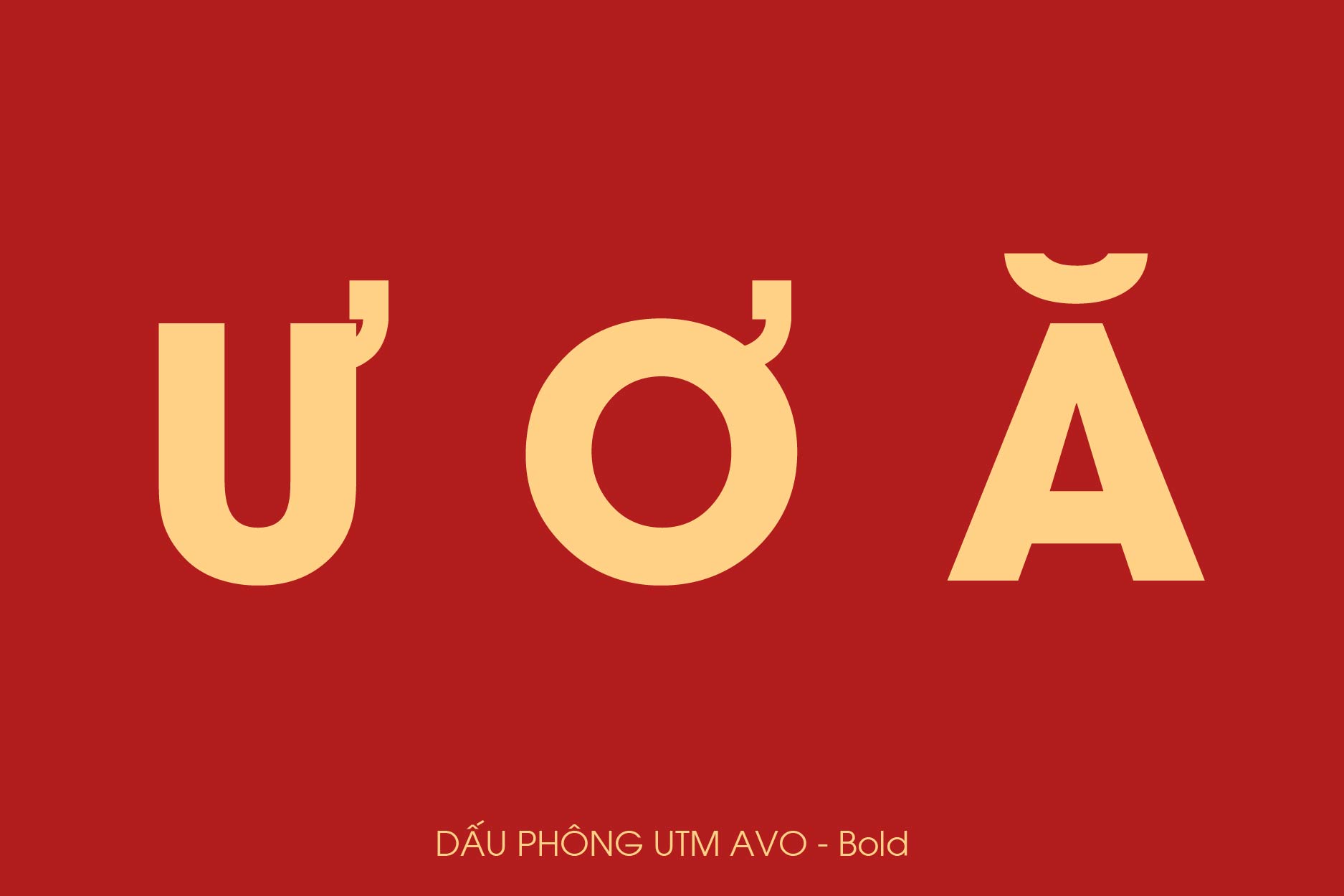
Font SVN Avo việt hóa là font chữ sans-serif hiện đại, thanh lịch thuộc bộ font SVN phổ biến trong giới designer Việt Nam. Font chữ này được sử dụng rộng rãi trong thiết kế thương hiệu, poster quảng cáo, website và tài liệu doanh nghiệp nhờ nét mảnh, chuyên nghiệp và khả năng hiển thị tốt trên mọi nền tảng.
Font SVN Avo việt hóa là gì?
Font SVN Avo thuộc bộ font SVN (SVN Fonts Việt Nam) được thiết kế với phong cách hiện đại, minimalist, mang hơi hướng của các font sans-serif geometric phương Tây. Font này đặc biệt phổ biến trong giới designer Việt Nam nhờ sự kết hợp hoàn hảo giữa tính thẩm mỹ và khả năng hiển thị tốt trên cả màn hình và in ấn.
SVN Avo có nét mảnh, thanh lịch với các đường nét cân đối, tạo cảm giác nhẹ nhàng nhưng vẫn đủ mạnh mẽ để làm nổi bật thương hiệu. Font này tương thích đầy đủ với tiếng Việt, hỗ trợ tất cả dấu thanh (á, à, ả, ã, ạ, ă, ắ, ằ, ẳ, ẵ, ặ, â, ấ, ầ, ẩ, ẫ, ậ…) mà không bị lỗi hiển thị hay thiếu ký tự.
Bộ font SVN Avo bao gồm các phiên bản chính:
Một số nguồn cũng đề cập đến các phiên bản mở rộng như SVN Avo Light, SVN Avo Medium (nếu có), tuy nhiên 4 phiên bản trên là phổ biến và được sử dụng nhiều nhất trong thiết kế.
Tên phiên bản |
Font weight | Kiểu chữ |
Ứng dụng tốt nhất |
SVN Avo Regular |
400 | Thường | Body text, nội dung chính website, brochure. |
SVN Avo Italic |
400 | Nghiêng | Trích dẫn, chú thích, ghi chú. |
SVN Avo Bold |
700 | Đậm | Logo, tiêu đề, heading, poster (18-48pt). |
SVN Avo Bold Italic |
700 | Đậm nghiêng | Tiêu đề phụ có nhấn mạnh đặc biệt. |
- Phong cách: Sans-serif geometric, hiện đại, minimalist.
Ứng dụng font SVN Avo trong thiết kế thương hiệu
Font SVN Avo mang phong cách hiện đại, thanh lịch, được ưa chuộng trong thiết kế thương hiệu cao cấp:
- Nét mảnh, thanh lịch, hiện đại: Font SVN Avo có các đường nét mảnh, cân đối, tạo cảm giác nhẹ nhàng, tinh tế nhưng vẫn đủ rõ ràng để đọc. Đây là lựa chọn lý tưởng cho thương hiệu muốn truyền tải hình ảnh hiện đại, chuyên nghiệp.
- Phù hợp thương hiệu cao cấp: Phong cách minimalist của SVN Avo phù hợp đặc biệt với các thương hiệu thời trang, công nghệ, kiến trúc, nội thất, mỹ phẩm cao cấp – những ngành hướng đến khách hàng có gu thẩm mỹ tinh tế.
- Dễ đọc, chuyên nghiệp: Khoảng cách ký tự và chiều cao chữ được tối ưu tốt, giúp nội dung dễ đọc trên cả website, tài liệu in và slide thuyết trình.
- Kết hợp tốt với font serif: SVN Avo Bold thường được dùng cho heading, kết hợp với font serif như Times New Roman, Playfair Display cho body text, tạo sự tương phản và phân cấp thông tin rõ ràng.
Font SVN Avo xuất hiện rộng rãi trong nhiều dự án thiết kế chuyên nghiệp:
- Logo thương hiệu thời trang cao cấp, công ty công nghệ, startup sáng tạo.
- Poster quảng cáo sản phẩm, brochure giới thiệu doanh nghiệp.
- Website doanh nghiệp hiện đại, landing page, portfolio cá nhân.
- Báo cáo thường niên, annual report, tài liệu nhà đầu tư.
- Slide thuyết trình chuyên nghiệp cho hội thảo, pitch deck startup.
- Bao bì sản phẩm cao cấp: mỹ phẩm, nước hoa, đồng hồ, phụ kiện.
- Magazine, catalogue thời trang, kiến trúc, nội thất.
- Social media branding: Instagram, LinkedIn, Facebook business page.
- Menu nhà hàng cao cấp, fine dining, khách sạn boutique.